Принципы измерения и терминология
Существуют две системы типографских измерений: англо-американская система, или система Пика (Pica), и система Дидо (Didot).
Система Пика применяется в Великобритании, Америке и в большинстве стран остального мира, кроме континентальной Европы. Система Дидо применяется в большинстве стран континентальной Европы и в России. В обеих системах основной единицей измерения является типографский пункт (point); но в то время как в англо-американской системе он равен округленно 0,351 мм, пункт в системе Дидо чуть больше – округленно 0,376 мм.
Величина шрифта в наборе выражается в кеглях. Размер кегля определяется в пунктах. Поскольку эти понятия складывались во времена металлического набора, кеглем считается величина площадки, на которой размещается буква (знак). Например, кегль 10 пунктов равен 3,76 мм (3,51 мм в системе Пика), но само очко знака, естественно, меньше, так как необходимо предусмотреть место для надстрочных и подстрочных элементов знака (диакритических знаков).
Профессиональные наименования кеглей различного размера широко употребляются до сих пор в типографском деле и фигурируют в специальной литературе:
- кегль 3 пункта – бриллиант
- кегль 4 пункта – диамант;
- кегль 6 пунктов – нонпарель;
- кегль 7 пунктов – миньон;
- кегль 8 пунктов – петит;
- кегль 9 пунктов – боргес;
- кегль 10 пунктов – корпус;
- кегль 12 пунктов – цицеро;
- кегль 14 пунктов – миттель.
В большинстве современных фотонаборных систем применяется преобразование пунктов и пик в миллиметры или дюймы. Они более удобны для типографских измерений при наборе, нежели пункты и пики, например, если необходимо задать точный размер заголовка или осуществить набор в строго ограниченном пространстве.
Для облегчения дальнейших вычислений можно пользоваться следующей таблицей перевода.
Во времена металлического набора строки отделялись одна от другой физически – вставкой пробельного элемента шириной в два пункта (так называемого шпона).
Соотвественно, характеристика набора должна была содержать название гарнитуры (например, Таймс), величину кегля (например, 10 пунктов) и количество шпон для указания интерлиньяжа (например, на два шпона, или 10 на 12).
В современных технологиях нет необходимости задавать размеры этим традиционным способом, поскольку фотонаборное изображение не имеет ограничений, свойственных металлическому набору: изображение может быть достаточно точно помещено в любое место, однако традиционный способ все еще используется, даже в фотонаборных системах, поскольку позволяет гибко переходить от одних единиц измерения к другим: миллиметрам, дюймам, цицеро, пикам или пунктам.
При задании больших размеров литер или литер, "плавающих" внутри определенной зоны, часто бывает удобнее использовать в качестве размера высоту строчной буквы х для данной гарнитуры (x-heights) или высоту прописных букв (cap-heights), или же ширину столбца (measures); все эти размеры лучше выражать в миллиметрах или в дюймах. Задавать позицию литер внутри пустого пространства легче в миллиметрах или в дюймах, чем в пиках и пунктах.
Любая буква, цифра или знак наборного алфавита носит название символ (character) или литера (sort). Размер символа в пунктах измеряется в соответствии с определенным для него типом единицы измерения, и отсчитывается от вершины выступающего над символом выносного элемента до конца нижнего выносного элемента. Ширина символа в различных шрифтах одного размера может существенно меняться. Изготовители шрифтов используют различные способы задания ширины для каждого из символов шрифта: чаще всего они используют в качестве единиц измерения доли ширины строчной буквы "m". Для монотипных шрифтов, например, "m" делится на 96 долей, а для выражения ширины каждого символа используется количество этих долей.
Половина значения ширины "m", называемая "n", применяется в качестве единицы измерения ширины для наборных шрифтов. Для среднего наборного шрифта с размером 11 пт единица ширины "n" составит 5 пт, или 1,75 мм, т.е.
на одном дюйме уместится чуть больше 14 символов. Для сравнения в печатающих машинках в одном дюйме размещается 10 или 12 символов (см. раздел 5.1.2). Ниже показаны некоторые из характеристик, описывающих печатные символы.
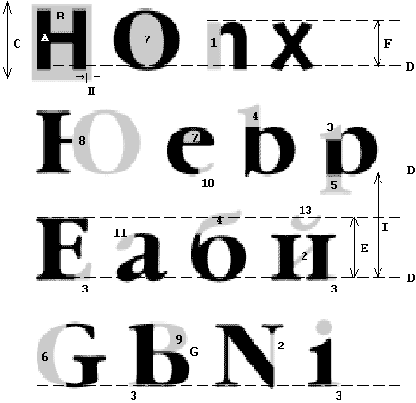
Рис. 2.1. Анатомия буквы и ее элементы
А – очко литеры (Face of Character).
B – кегельная площадка (Em-Square).
C – кегль (Size).
D – линия шрифта (Baseline).
E – высота (рост) прописного знака (Cap-height).
F – высота (рост) строчного знака (x-height).
G – межбуквенный просвет (Letterspace).
H – полуапрош (Side bearing).
I – интерлиньяж (Linespace).
- oсновной штрих (Stem).
- соединительный штрих (Hairline).
- засечка, сериф (Serif).
- верхний выносной элемент (Ascender).
- нижний выносной элемент (Descender).
- наплыв (Stress).
- внутрибуквенный просвет (Counter).
- овал (Oval).
- полуовал (Bowl).
- концевой элемент (Terminal).
- каплевидный элемент (Ball).
- точка (Dot).
- диакритический знак, акцент (Accent).
Для цифр обычно используется выравнивание (они имеют ту же высоту, что и заглавные буквы); но могут применяться и разновысокие цифры (высота цифры равна высоте строчной буквы с верхним выносным элементом), что лучше сочетается со строчными буквами.
Знаков препинания, используемых в типографском деле, гораздо больше, чем применяемых для пишущих машинок и текстовых процессоров. Дефисы, разделители в виде длинного или среднего тире различны по виду и имеют разное предназначение. Дефис представляет собой короткую черту шириной примерно в одну четверть единицы ширины "m", он используется для соединения частей составных слов и переносов слов в конце строки. Символ тире более тонкий и длинный, ширина его составляет половину единицы ширины "m" (в два раза больше, чем для дефиса), и он используется для написания дат (1997–98) и при отображении списков в качестве маркера.
Длинное тире используется с той же целью, что и скобки.
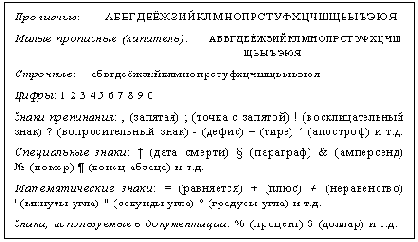
Рис. 2.2. Основные составляющие стандартного шрифтового комплекта
Гарнитуры описывают полный набор шрифтов, имеющих символы аналогичного дизайна, но различных размеров (8 пт Helvetica Medium, 9 пт Helvetica Medium, 10 пт Helvetica Medium и т.д.).
Семействами называются серии шрифтов, похожих друг на друга по дизайну, но различающихся в отдельных элементах: наклон, насыщенность или ширина символов. Основными составными элементами семейства могут быть курсив (italic) и полужирный (bold). По насыщенности шрифты могут быть сверхсветлыми (extra-light), светлыми (light), нормальными (normal), средними (medium); полужирными (bold), жирными и сверхжирными (extra-bold); по ширине символов – сверхузкими, нормальными, широкими и сверхширокими.
Компьютерные программы набора могут использовать эти эффекты для создания наклона, сжатия, расширения или придания тени для любого символа в тексте.
Символы в строке располагаются в пределах заданной линии, а сами строки могут быть выровнены влево, вправо или центрированы (выключка влево, вправо, по центру). Обычно при наборе строка выравнивается по всей ширине блока (по формату); при наборе с выравниванием влево строка занимает не всю отведенную для нее ширину, оставляя свободное пространство справа.
Межсловные пробелы в строке могут быть либо фиксированными, в случае, когда не применяется выравнивание по ширине , либо переменными, в случае выключки по формату (по ширине). Величина фиксированных пробелов устанавливается пропорционально ширине "m" для данного шрифта. Обычно для текста применяется средняя величина межсловных пробелов или половина средней ширины "m" символа.
При выключке по формату, где межсловные пробелы варьируются, чтобы обеспечить одинаковую длину строк, минимальный пробел соответствует "малому промежутку", или 20% от "m", и может достигать величины "m" или даже более – хотя строка выглядит при этом разреженной.К этим параметрам мы вернемся в разделе 2.4.